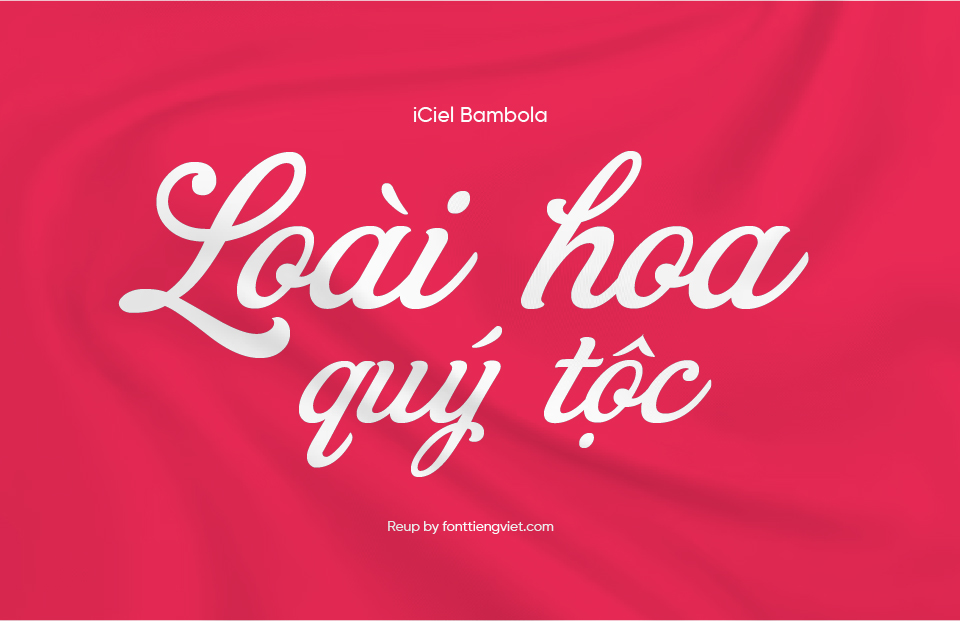
Font việt hóa iCiel Bambola – Bộ font viết tay điệu đà cho thiết kế chuyên nghiệp
Giới thiệu về Font việt hóa iCiel Bambola
Trong cộng đồng thiết kế đồ họa tại Việt Nam, nhu cầu tìm kiếm một Font Chữ vừa mang nét mềm mại, vừa đảm bảo tính thẩm mỹ cao luôn là ưu tiên hàng đầu. Font việt hóa iCiel Bambola chính là sự lựa chọn hoàn hảo cho những ai yêu thích phong cách viết tay thanh thoát và đầy nữ tính. Đây là một bộ font script hiện đại, được đội ngũ iCiel chăm chút kỹ lưỡng để phù hợp hoàn toàn với bảng mã Unicode tiếng Việt.
Đặc điểm nổi bật của bộ Font việt hóa iCiel Bambola
Nét vẽ thủ công độc đáo
Đặc điểm nhận dạng của iCiel Bambola chính là những đường nét uốn lượn tự nhiên như được vẽ trực tiếp bằng bút mực. Các ký tự có độ dày mỏng linh hoạt, tạo nên cảm giác gần gũi và chân thực cho người xem.
Tính ứng dụng đa dạng trong thực tế
Nhờ vẻ ngoài điệu đà, bộ phông này cực kỳ phù hợp cho các thiết kế thiệp mời đám cưới, bìa sách nghệ thuật, hoặc các ấn phẩm quảng cáo cho ngành làm đẹp. Sự tinh tế trong từng nét chữ giúp nâng tầm giá trị hình ảnh và tạo dấu ấn riêng biệt cho thương hiệu.
Để đạt hiệu quả thị giác tốt nhất, bạn nên sử dụng bộ font này cho các tiêu đề chính hoặc các đoạn văn ngắn. Việc kết hợp với các phông chữ không chân (Sans-serif) sẽ tạo ra sự tương phản hài hòa, giúp bố cục thiết kế trở nên cân đối và chuyên nghiệp hơn.